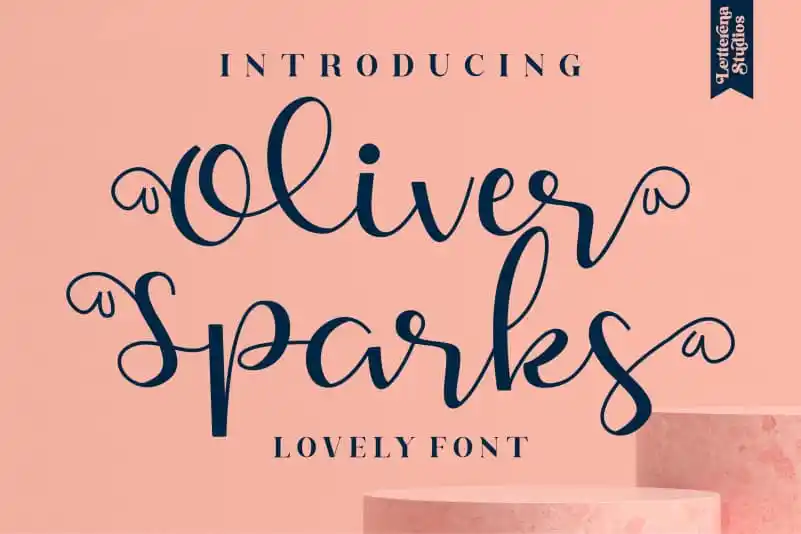
Oliver Sparks Script Font – Fonte Grátis
Oliver Sparks Script Font
A fonte “Oliver Sparks Script Font” oferece uma experiência única e romântica para projetos que exigem elegância e sofisticação. Ideal tanto para logos quanto para designs de produtos, como etiquetas e embalagens, esta fonte elegante combina perfeitamente com estilos criativos para homenagens, convites de casamento, cartões de presente, materiais de embalagem e até mesmo retratos artísticos. Sua forma fluida e delicada faz dela uma opção favorita entre designers que buscam um toque de romanticismo em qualquer projeto onde ela for aplicada. A “Oliver Sparks Script Font” é perfeita para aqueles que desejam dar a sua arte um ar ainda mais sofisticado, transformando as tarefas diárias em verdadeiros trabalhos de arte.